もじモジ探偵団 文字バンザイ編 まちで見かける文字デザインの秘密
グラフィック社は、雪朱里氏著書で、ヒグチユウコ氏がイラストを手掛けた、くらしのなかで目にするさまざまな文字のデザインは、いつ、どこで、だれが手がけているの? を、アイアイ探偵と助手のネコくんが徹底調査し謎を解き明かす『デザインのひきだし』連載「もじモジ探偵団」の書籍化第2弾『もじモジ探偵団 文字バンザイ編 まちで見かける文字デザインの秘密』を、2025年5月に発売した。
だれもが見たことがあるお菓子のロゴや、生活の中で見ているさまざまな文字は、どれもが絶対に「誰か」がデザインしている。そんな色々な文字のデザインを丹念に探る 『デザインのひきだし』人気連載書籍化の第2弾が『もじモジ探偵団 文字バンザイ編 まちで見かける文字デザインの秘密』となる。
ドン・キホーテの店頭のPOPは、実は全店舗にPOPライターがいて、全て手書きしている。
そのワケやどうやって書いているかなどを、豊富な写真と文章で紹介。
また、本書の挿画も手掛ける大人気画家・ヒグチユウコ氏の描き文字を、アドビのタイプデザイナー・西塚涼子氏が画期的なシステムでフォント化した書体「ヒグミン」の制作に密着した「フォントつくるぞ! ヒグミン編」も収録。
文字が気になる人必見の1冊となる。
『もじモジ探偵団 文字バンザイ編 まちで見かける文字デザインの秘密』イメージ
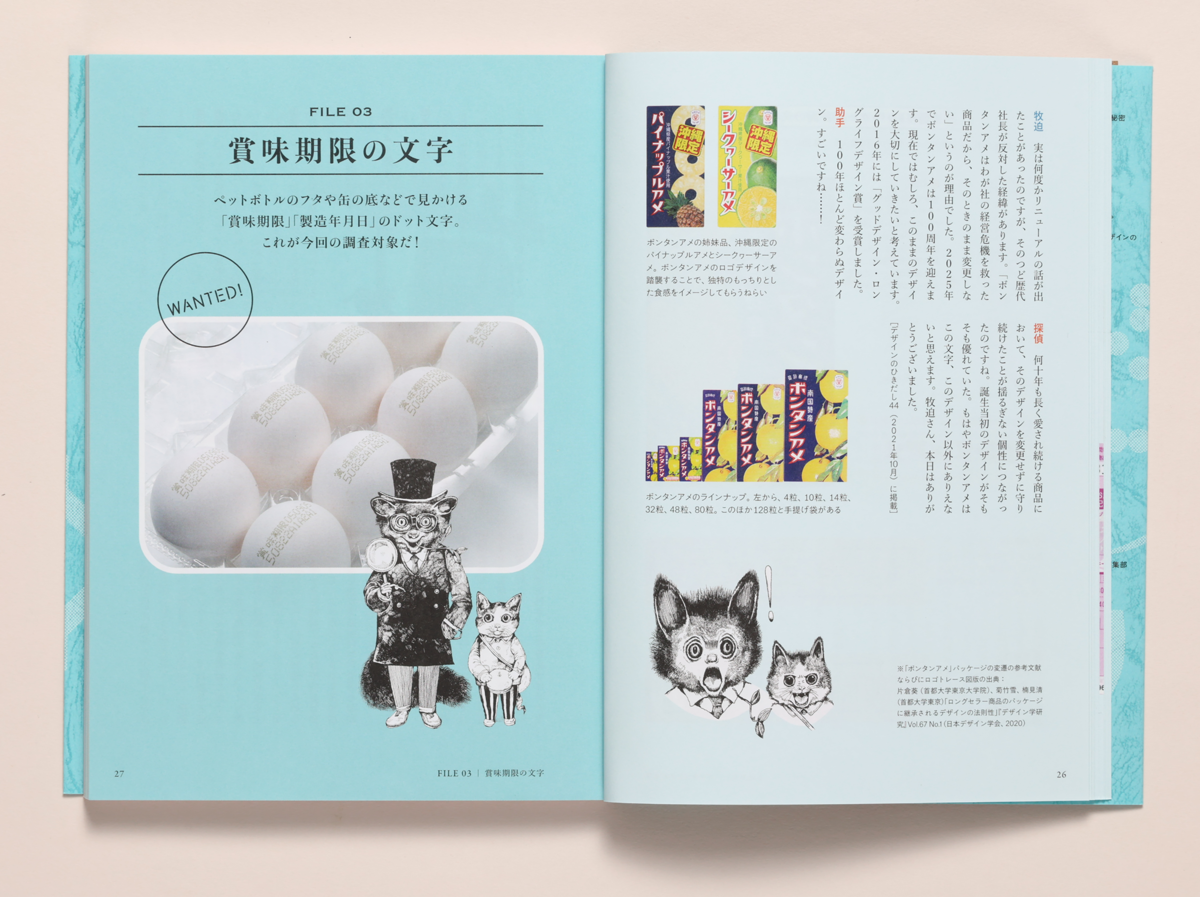
左)ペットボトルのフタなどで見かける「賞味期限」のドット文字 右)誰もが一度は見たことあるボンタンアメの文字
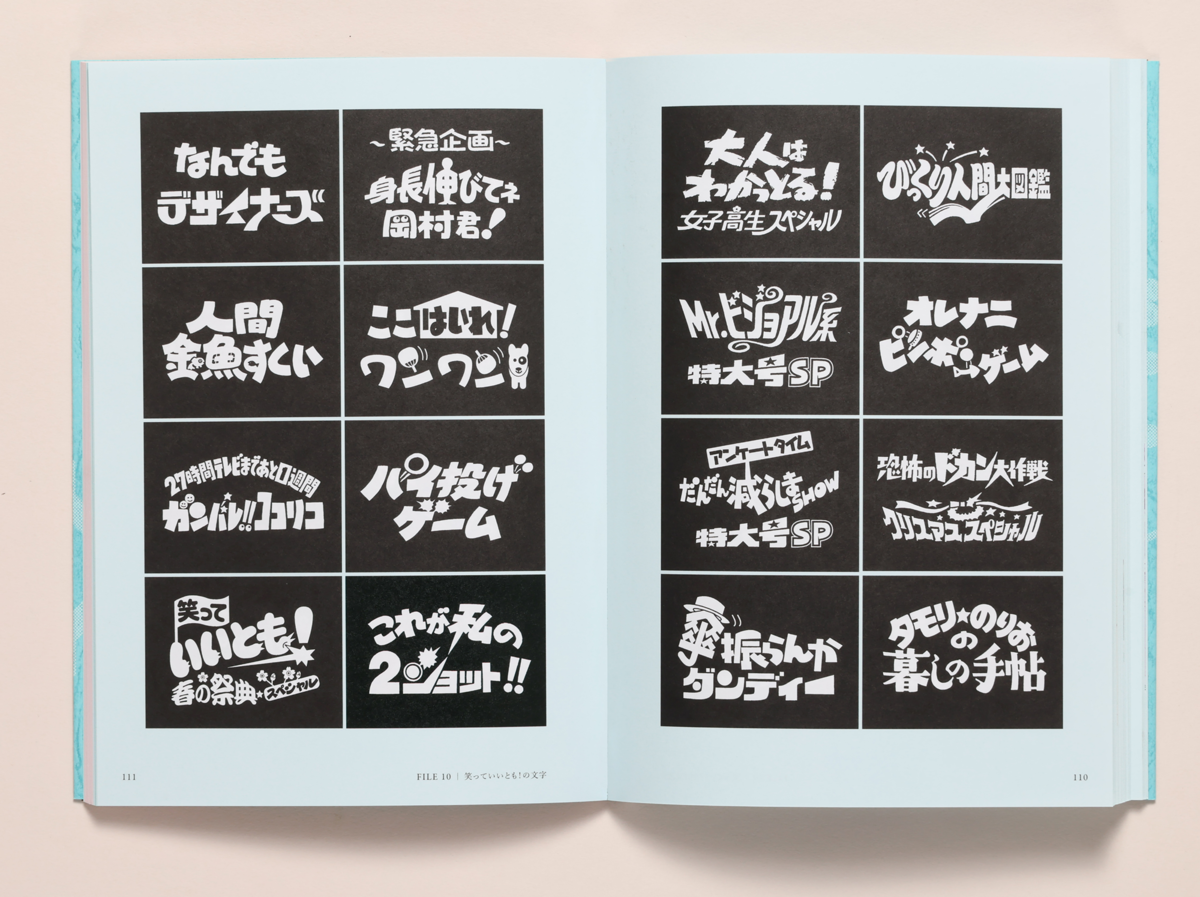
人気テレビ番組だった「笑っていいとも!」の描き文字
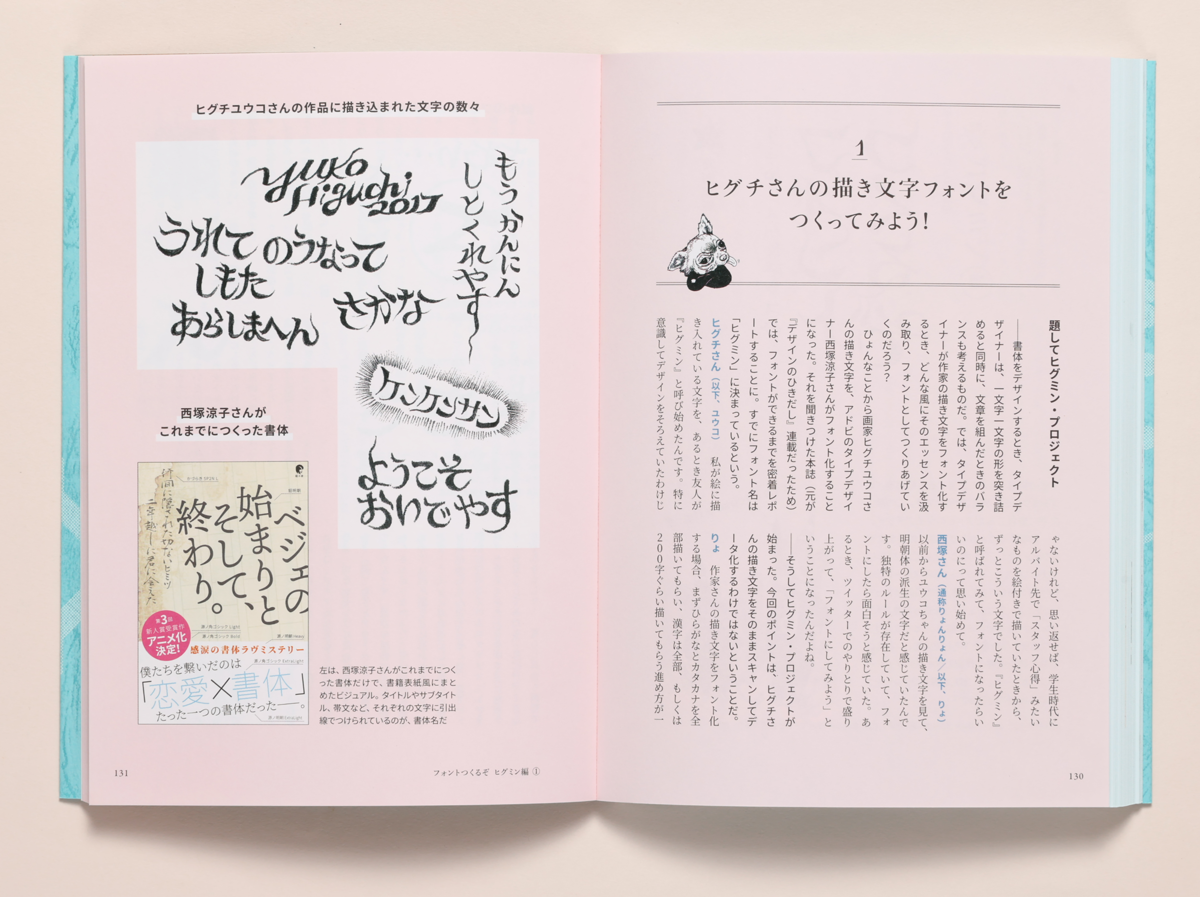
アドビのタイプデザイナー・西塚涼子さんがヒグチユウコさんの描き文字をフォント化した「フォントつくるぞ! ヒグミン編」